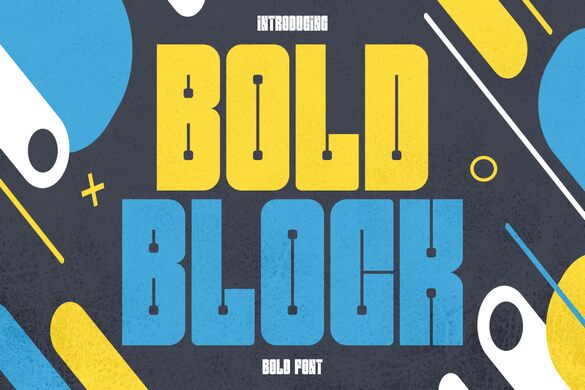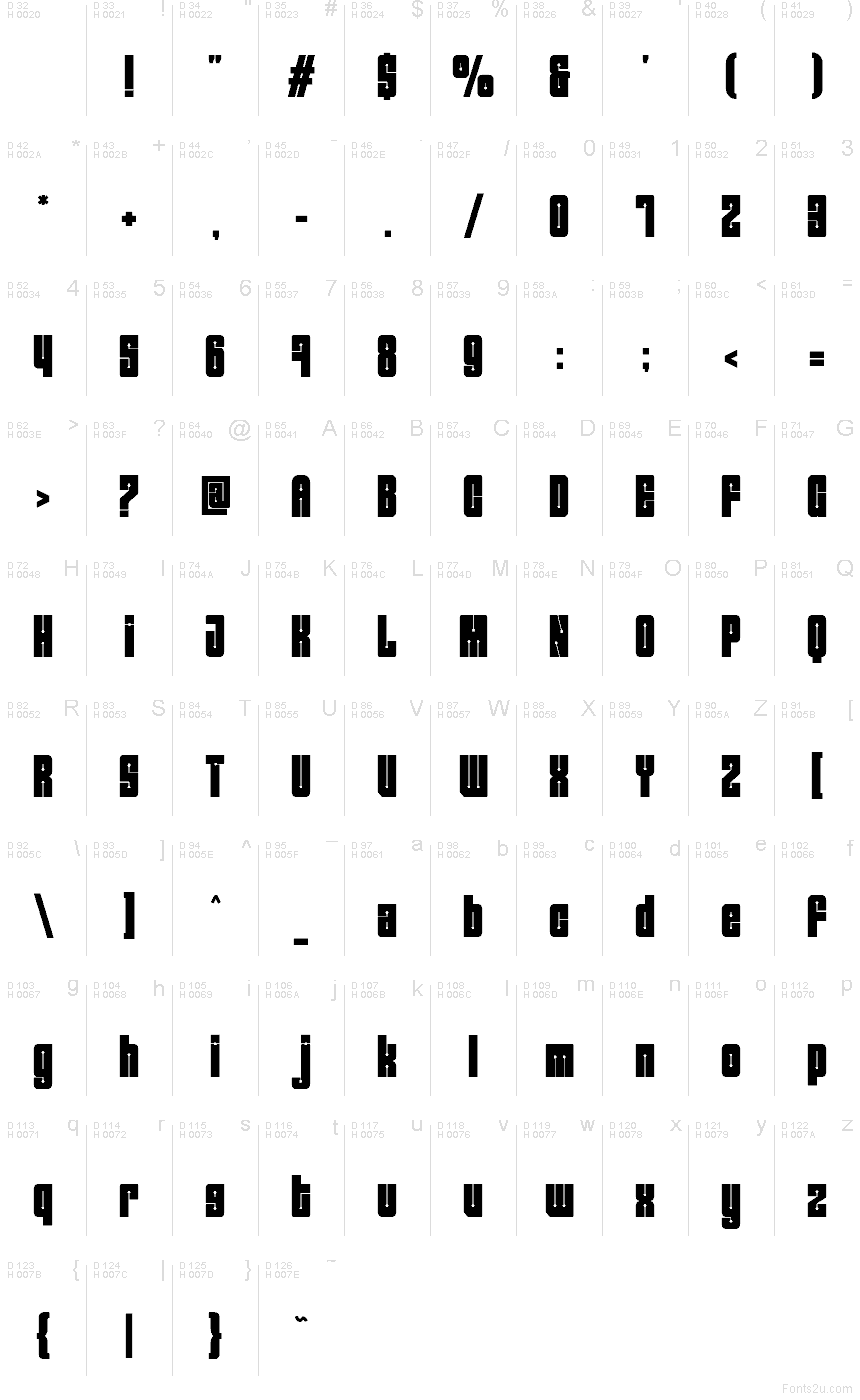
Bold Block, die moderne, kostenlose Block-Display-Schrift von Shanaf Studio, besticht durch ihre wuchtige, plakative Silhouette. Mit ihrer massiven schwarzen Fläche und den schmalen, weißen Aussparungen in der Mitte der Buchstaben wirkt sie kompakt und ausdrucksstark. Die abgerundeten Formen verleihen dem Alphabet jedoch einen weichen Charakter, der ihr statt rein geometrischer Strenge einen charmanten Retro-Look verleiht.
Diese kostenlose Schrift ist ideal überall dort, wo Buchstaben wie ein grafischer Block wirken sollen – sei es auf Musikplakaten, in der Streetwear-Branche, bei Cover-Designs, Titelschriftzügen oder auf Verpackungen. Dank der markanten Schlitze in den Buchstaben eignet sie sich zudem hervorragend für kurze Schriftzüge und Monogramme, denen sie eine unverwechselbare Rhythmik verleiht.